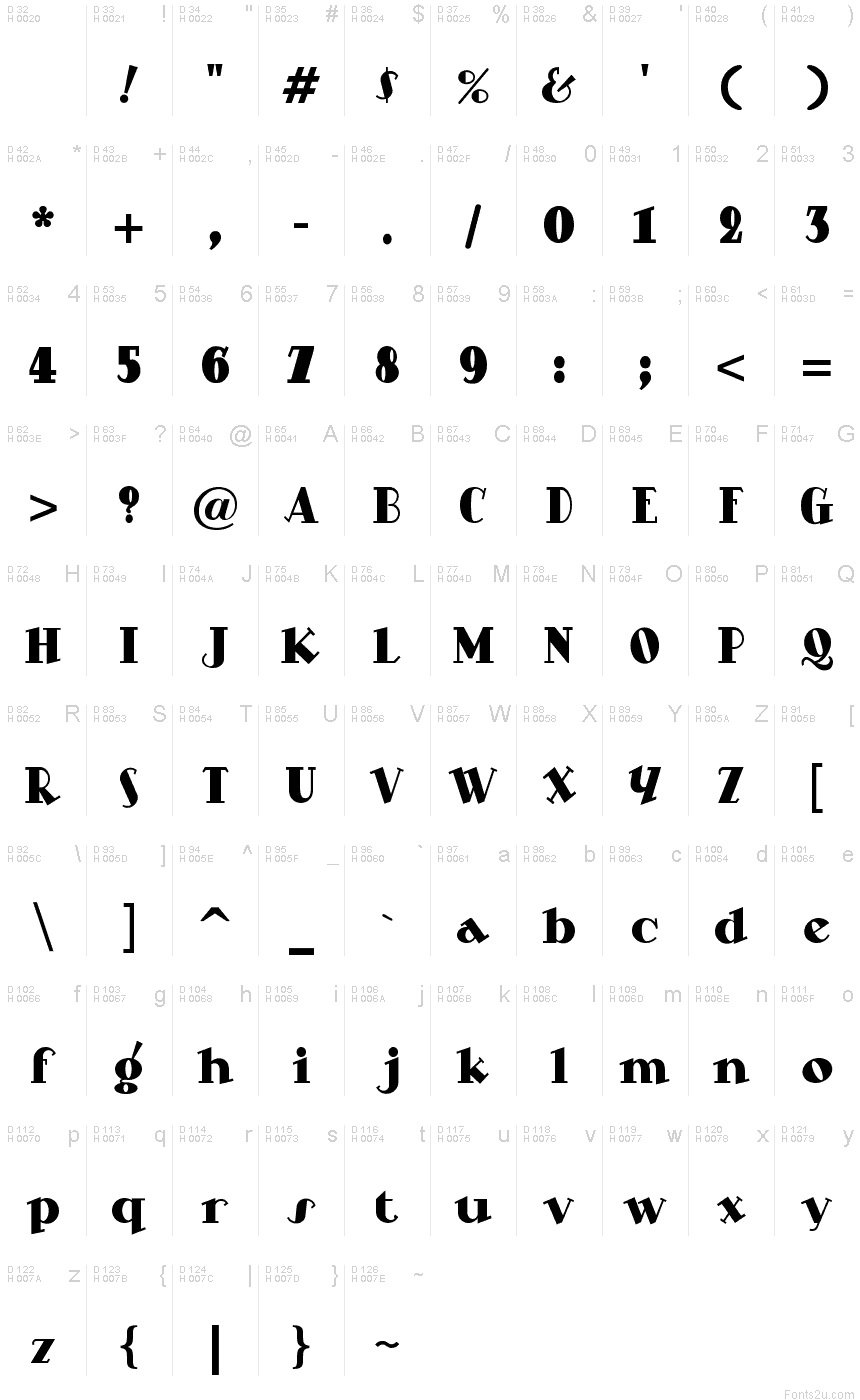
Steppin Out, autorstwa Nicka Curtisa, to darmowy, retro krój displayowy z energią neonowych szyldów z lat 20. XX wieku. Litery łączą w sobie szerokie, „atramentowe” krzywizny z ostrymi, zdecydowanymi cięciami i zawadiackimi przekątnymi, co nadaje całości elegancki, taneczny rytm, który sprawia wrażenie teatralnego, a nie tylko nostalgicznego.
Krój ten świetnie pasuje do nagłówków plakatów, menu koktajlowych, ulotek eventowych, okładek albumów i szyldów sklepowych, wszędzie tam, gdzie odrobina dawnego wielkomiejskiego glamouru pomoże zbudować klimat. Jako darmowy font, Steppin Out sprawdza się również w kartach tytułowych, krótkich nazwach na opakowaniach i wyróżnionych cytatach, zwłaszcza gdy szukasz żywego kontrastu między soczystymi krzywiznami a ostrymi, wyciętymi kątami.